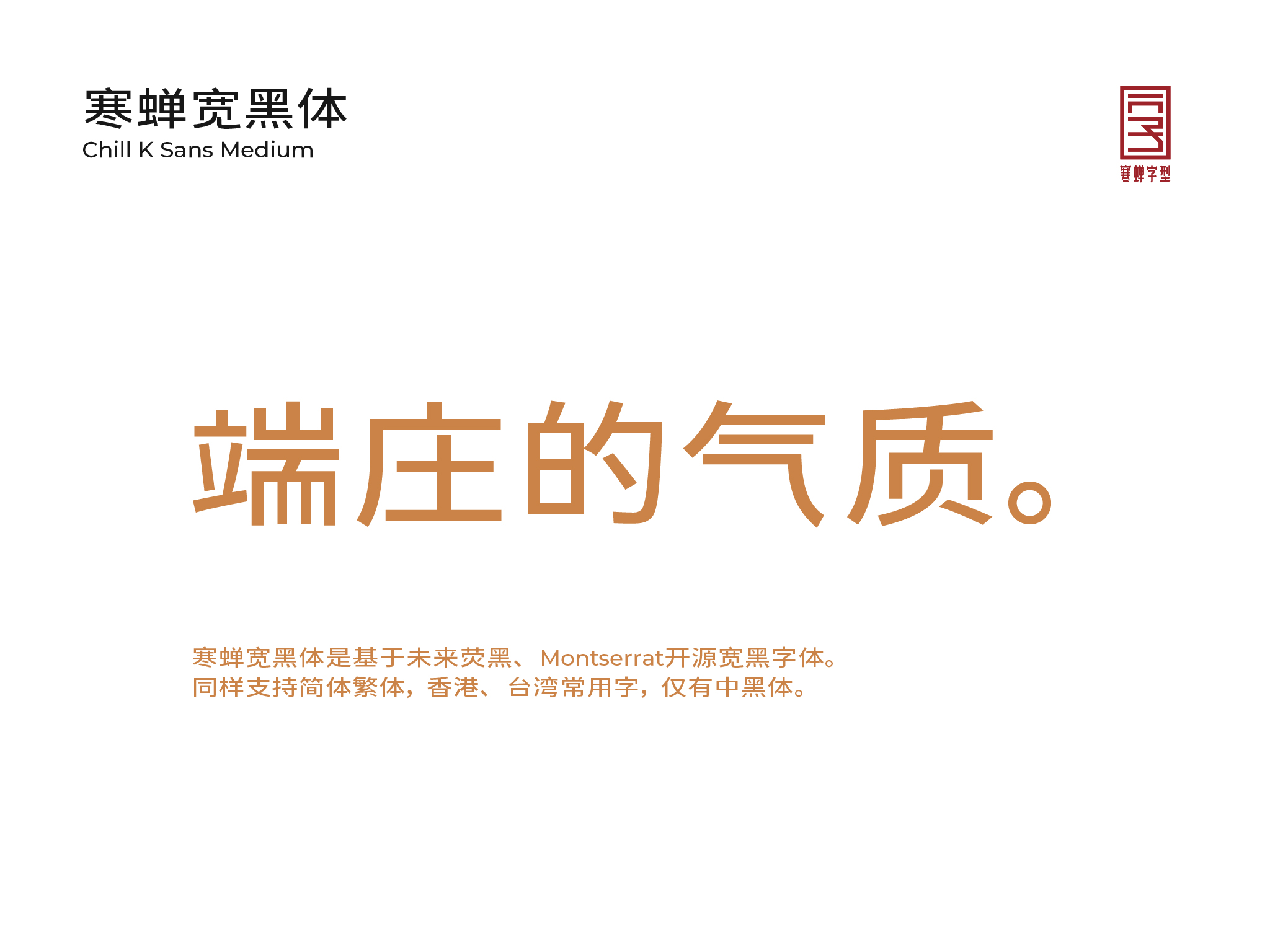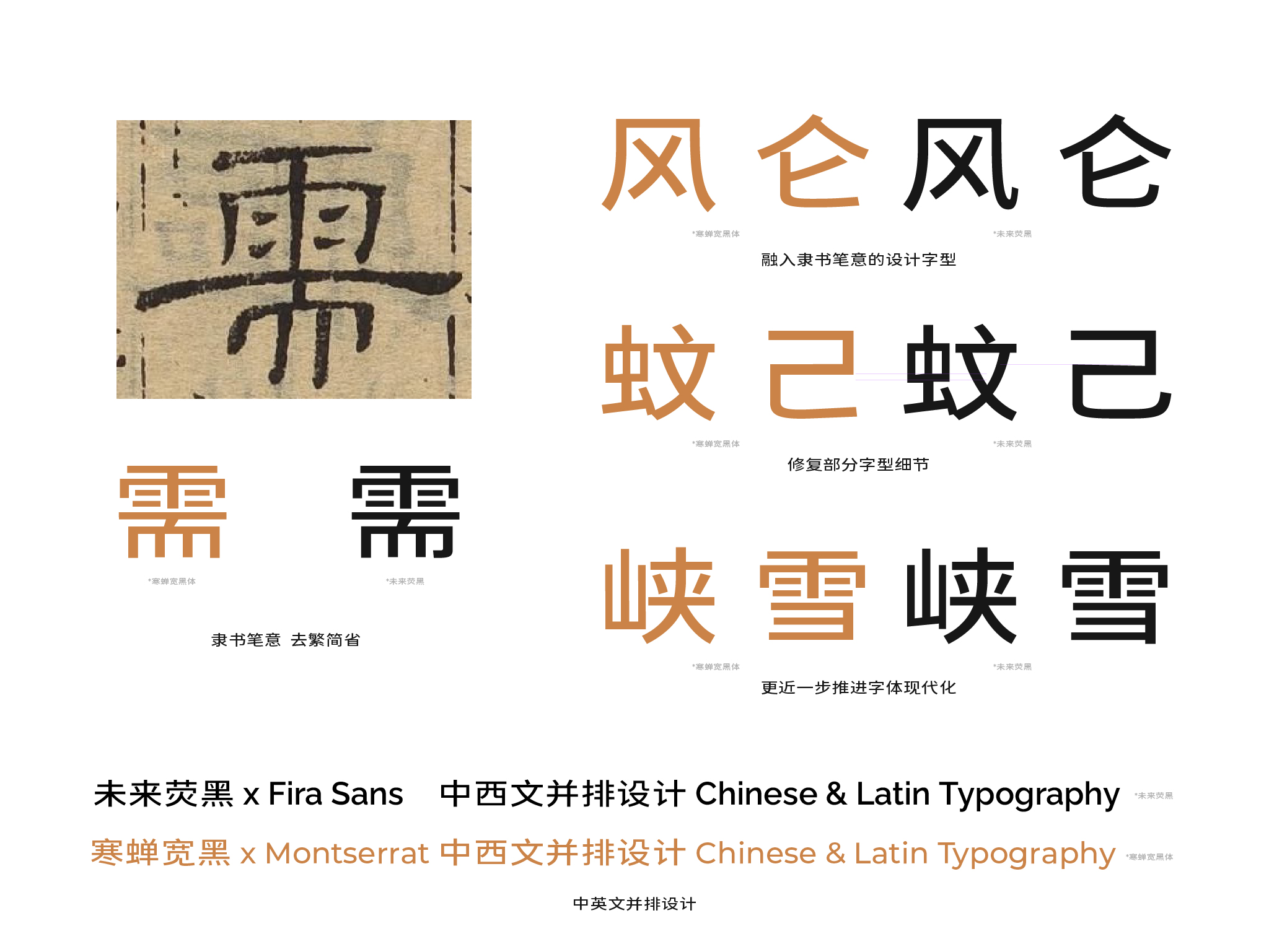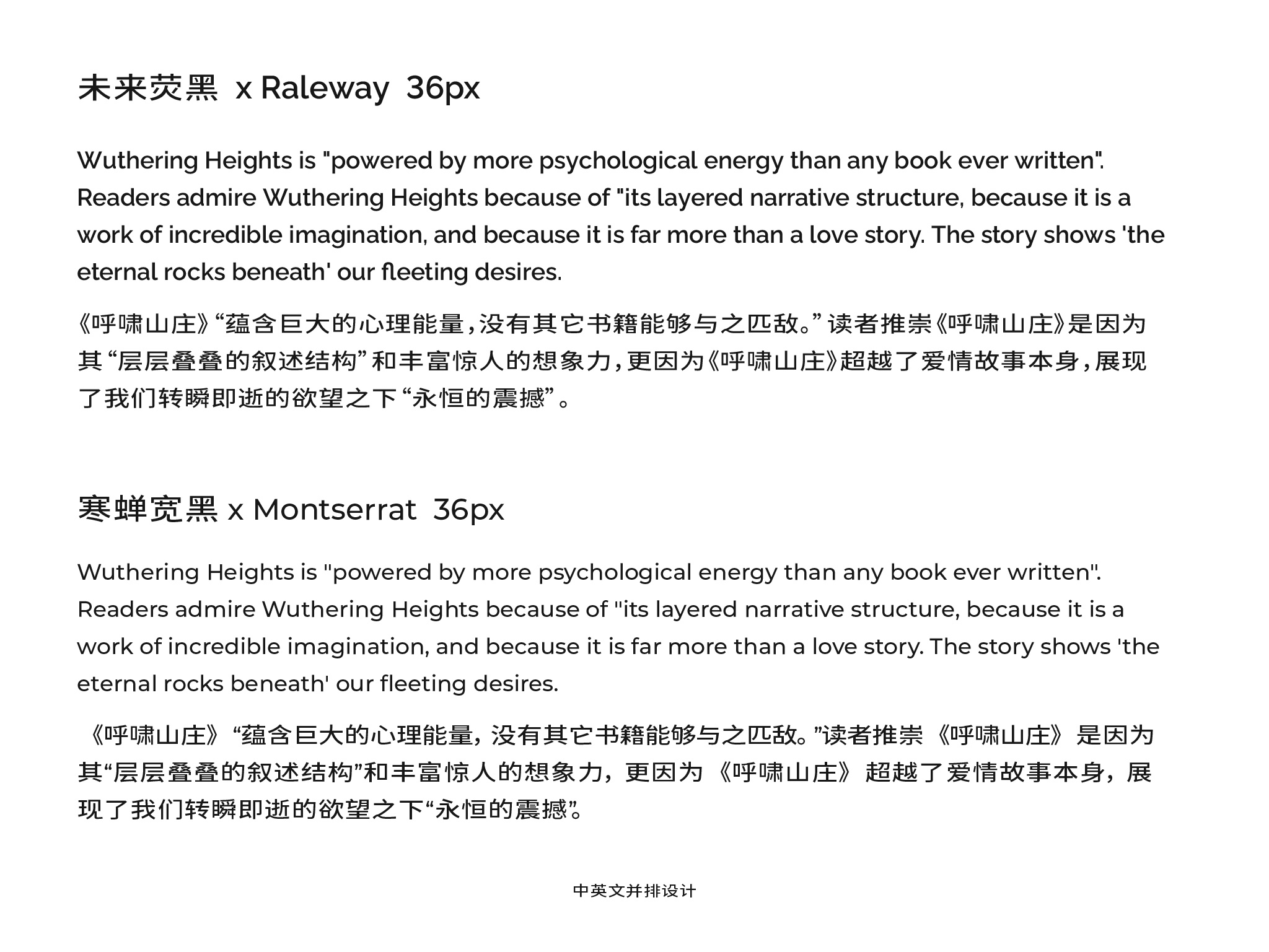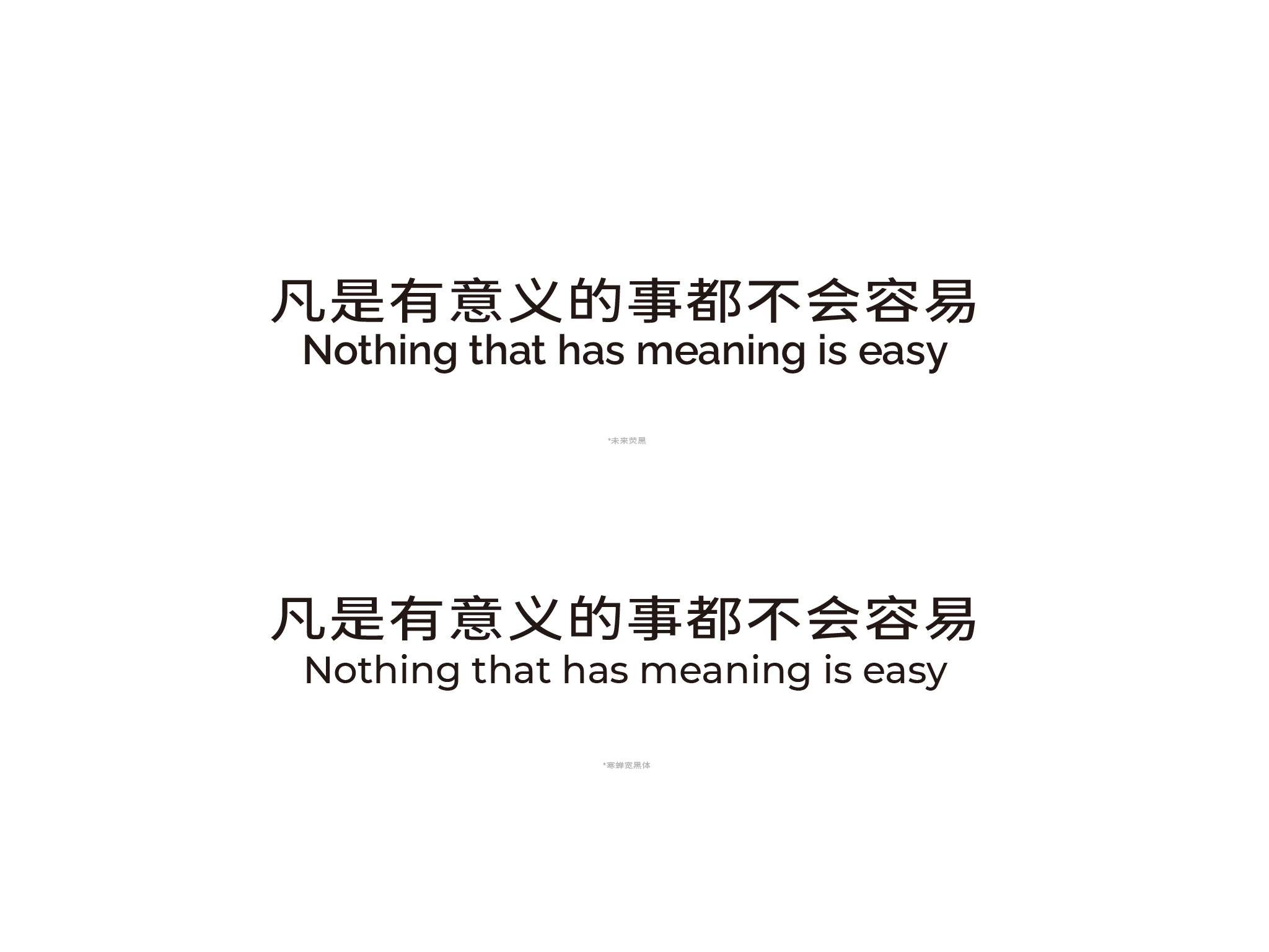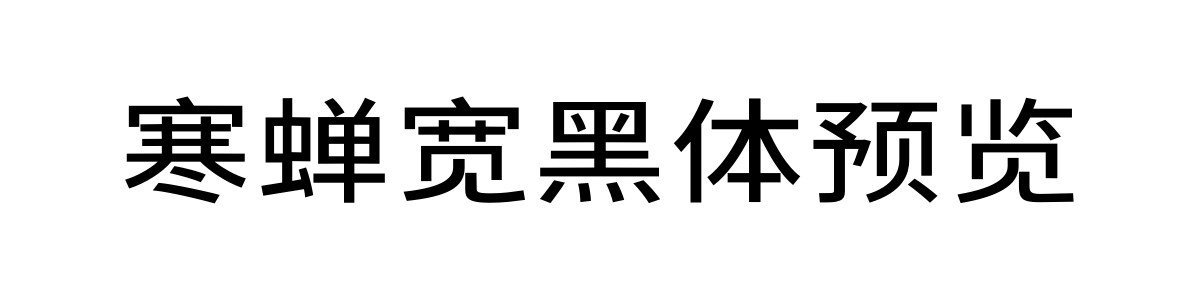
寒蝉宽黑体
寒蝉宽黑体(Chill K Sans)是一款在现代黑体骨架中融入微妙“隶意”,专为大幅面标题与版式设计的开源中文字体。基于“未来荧黑”进行深化设计,而“未来荧黑”本身又源于对“思源黑体”的参数化算法调整。寒蝉宽黑体在继承了这一现代、简明造型基因的基础上,关键性地加入了传统书法中的“隶意”笔画特征,并优化了字型结构的避让关系,使其视觉效果更为简洁、干净。
开发团队手动检查并修复了前作中近8000个字符的轮廓细节,字符集覆盖简体中文、繁体中文、港澳台常用字及日文,并重新选用了开源字体 Montserrat 作为其西文搭配部分。
寒蝉宽黑体的风格可概括为“端庄现代,质朴平和”。它并非对传统隶书的直接复刻,而是在现代几何黑体的坚实骨架内,巧妙地点缀了隶书笔画的韵味。这主要体现在部分笔画(如撇、捺、钩)的起笔与收笔处,加入了微妙的弧度或顿笔处理,避免了纯粹几何线条的机械感,赋予字体一丝手写的温度与文化底蕴。